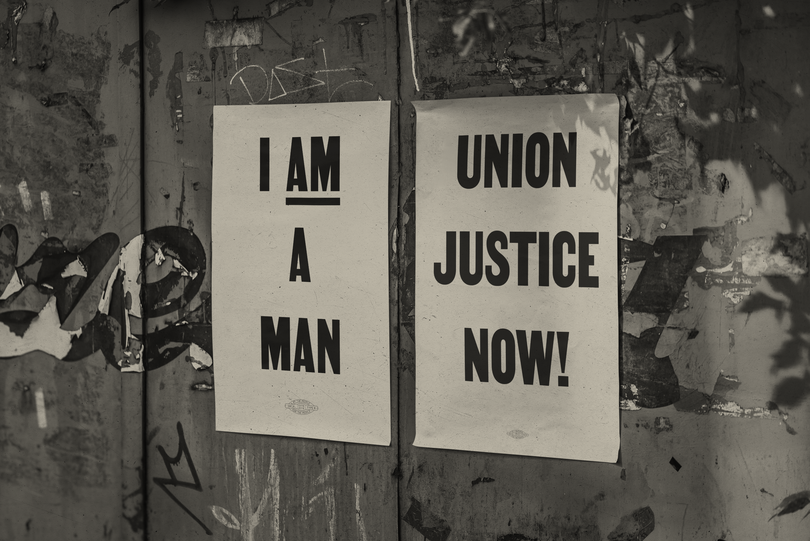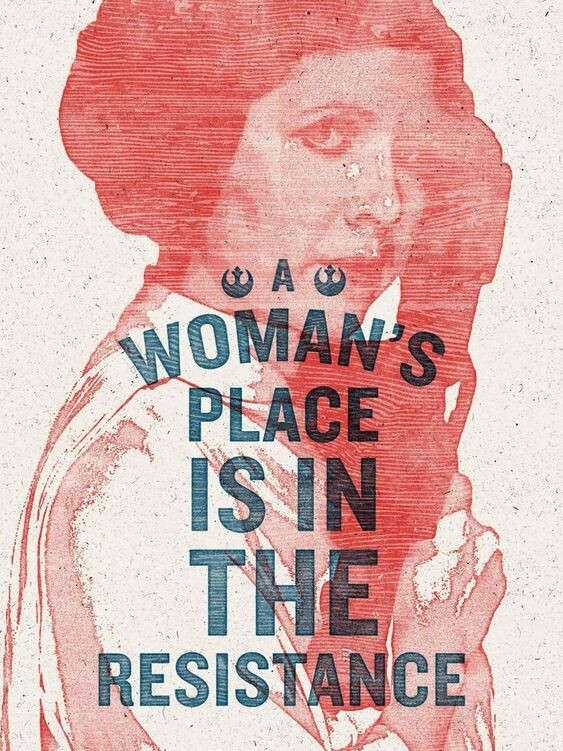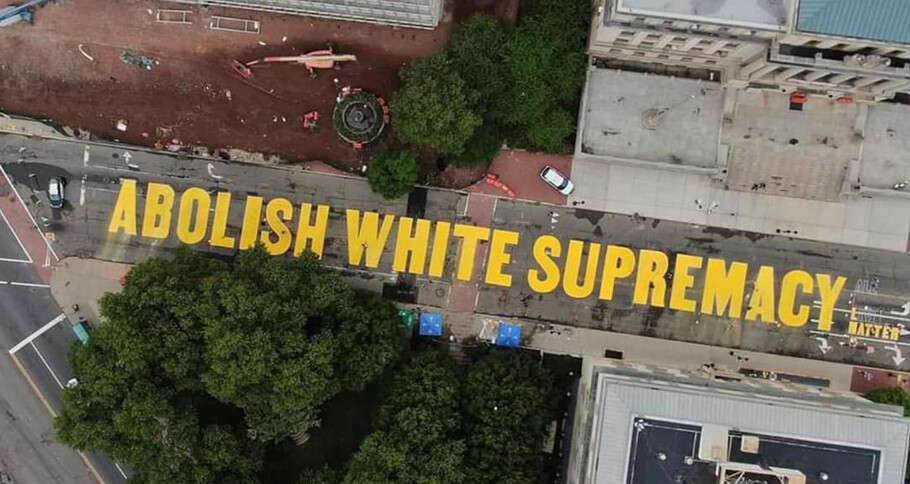
Des lettres dessinées à voix haute : Typographie et protestation moderne.
Rien ne saisit mieux la passion et la spontanéité de la contestation qu’une pancarte faite à la main. Souvent, l’urgence derrière une protestation implique la nécessité de simplement attraper un feutre et commencer à écrire.
Par essence, la typographie est un conteur. Les lettres délivrent des messages. C’est, probablement, lorsqu’ils sont dessinés par une communauté pour protester que ces messages sont à l’état le plus pur.
Même si la plupart de ceux qui fabriquent des pancartes et bannières pour des marches ou manifestations ne se considèrent pas comme designers graphiques, c’est exactement ce qu’ils deviennent, dans ce temps où ils forment des lettres sur des écriteaux. Chaque lettre est l’instantané d’une longue histoire, un message qui est à la fois hautement personnel et qui articule les pensées d’un mouvement plus vaste. Elles sont faites de colère et de tristesse, et distillent exactement ce que représente le meilleur design : le déclenchement d’un changement.
« Éliminer les fausses distinctions. »
L’histoire et le développement de l’imprimerie, et de la technologie des polices de caractères, ont joué un rôle majeur dans l’élaboration des outils de protestation et les messages diffusés. Pendant la seconde moitié du XXe siècle, des objets comme la presse à sérigraphies sont devenus plus accessibles et disponibles que jamais, et ont offert un parfait croisement entre les arts et l’activisme.
Même si la plupart de ceux qui fabriquent des pancartes et bannières pour des marches ou manifestations ne se considèrent pas comme designers graphiques, c’est exactement ce qu’ils deviennent, dans ce temps où ils forment des lettres sur des écriteaux.
Certains lieux se sont fait un nom en acceptant, pour des campagnes, des commandes avec délai de production rapide et aux tarifs abordables. C’est le cas du Poster Workshop à Camden Road (Londres) qui fut ouvert de 1968 à 1971. Proposant un service sans rendez-vous apprécié des grévistes, des groupes pour les droits civiques et des mouvements de libération comme la London Squatters Campaign, le collectif a dirigé l’atelier dans l’objectif d’encourager les réactions à un florilège de problèmes mondiaux et politiques, comme les droits des travailleurs, le conflit nord-irlandais et la Guerre du Vietnam.
Les styles, tout autant que les méthodes de production des designs finaux, font également partie d’une lignée historique. Prenez le mouvement féministe des années 60 et 70 : de nombreuses images semblent directement inspirées des communications du mouvement américain pour les droits civiques de la même époque. L’artiste Lucia Vernarelli a utilisé un style de gravure sur bois pour ses impressions qui est similaire à celui utilisé par Emory Douglas dans ses designs pour le Black Panther Party.
Cependant, pour sortir de la bulle de l’industrie créative, il n’est pas toujours utile de coller l’étiquette «design» dans le contexte des mouvements citoyens de protestation. L’universitaire Dori Tunstall a beaucoup écrit sur les principes d’anthropologie du design et comment ils peuvent être appliqués à l’organisation d’une communauté. Dans un essai publié en 2016 dans le Feminist Organization’s Handbook du Women’s Center for Creative Work, elle déclare que c’est vital pour le peuple « d’éliminer les fausses distinctions entre art, artisanat et design » de manière à remettre en cause les «hiérarchies» qui parviennent à se glisser au sein même de l’activisme communautaire.
Selon Tunstall, « l’activisme basé sur l’art reçoit une meilleure reconnaissance dans la presse et, souvent, davantage de soutien financier » suivi par « l’activisme basé sur l’artisanat… du fait de la perception d’authenticité locale » ; et puis, pour finir, « l’activisme basé sur le design arrive en dernier, puisqu’il est considéré comme trop «professionnel» par les citoyens mais trop «grand public» pour l’expression artistique. »
Elle souligne que c’est en grande partie le discours européen qui établit de telles distinctions : dans d’autres cultures, les gens font les choses simplement, sans considérer ce qu’ils sont ou quelle place ils prennent dans «la lutte».
Démocratiser le design : la communauté plutôt que la marque.
Durant la dernière décennie, ces distinctions se sont mélangées, estompées, pour ne pas dire presque évaporées. Depuis l’avènement des technologies digitales, la démocratisation des outils logiciels de création a permis à une approche moins égocentrique de prendre racine. Dans cet état d’esprit plus communautaire, les designers créent de plus en plus de travaux open source ou pouvant être téléchargés gratuitement.
L’une des forces du mouvement de la Marche des femmes, par exemple, c’est cette absence de marque ou d’identité visuelle particulière, telle que les grandes agences de communication pourraient les définir. Le mouvement est né aux États-Unis début 2017 à la suite de l’investiture de Donald Trump, et a grandi pour devenir une résistance mondiale envers le président américain et sa misogynie affichée, avant de s’ancrer davantage dans la société et le gouvernement.
Des images devenues emblématiques ont émergé de ce mouvement : l’affiche de Hayley Gilmore « La place d’une femme est dans la résistance » arborant du rouge et des lettres épaisses tout en majuscules ; et le symbole de Deva Pardue « Femme Fists ».
Image de couverture : Street Mural, Newark, NJ. Set in Martin by Vocal Type. Crédit photo : Isaac Jiménez.